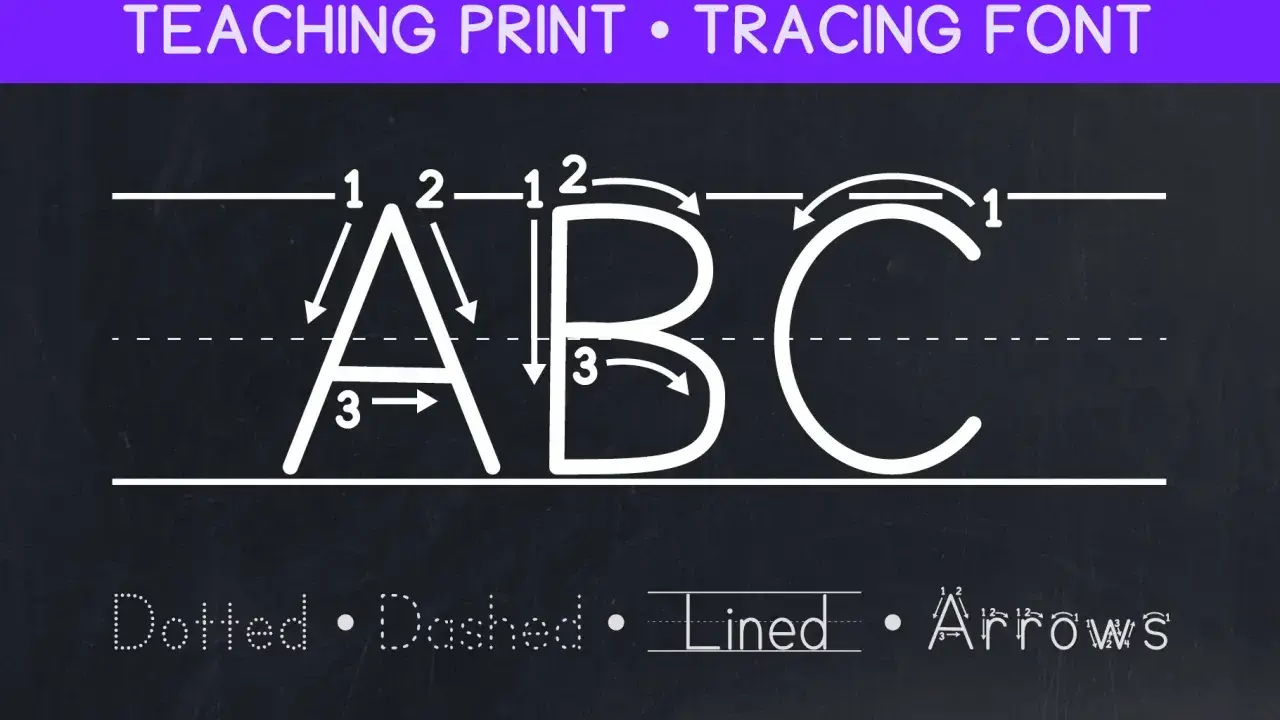
Szkolne pismo - Jak wybrać font, który wspiera naukę?
Pismo szkolne czcionka z literami ABC i strzałkami pokazującymi kierunek pisania. Pomoc w nauce pisania.
Szkolny krój pisma nie jest ozdobą, tylko narzędziem do nauki liter, łączeń i ruchu ręki. Dobrze dobrana czcionka potrafi ułatwić przepisywanie, pracę po śladzie i przygotowanie czytelnych kart pracy, a źle dobrana szybko zamienia ćwiczenie w zgadywanie kształtów. Poniżej pokazuję, jak rozpoznać sensowny krój, kiedy go używać i czego unikać, żeby materiał faktycznie wspierał naukę pisania.
Najlepsze efekty daje prosty krój, duży zapis i ograniczona liczba bodźców
• Szkolne pismo ma pomagać w nauce, a nie robić efekt typograficzny.
• Najlepiej sprawdzają się kroje z czytelnymi kształtami liter, wyraźnymi łączeniami i bez ozdobników.
• Do ćwiczeń po śladzie potrzebny jest większy zapis niż do zwykłego tekstu instrukcji.
• W kartach pracy ważniejsza od stylu jest czytelność po wydruku, także na domowej drukarce.
• Nie każdy font udający pismo ręczne nadaje się do nauki pisania.
Czym właściwie jest szkolne pismo i dlaczego nie każdy font się nadaje
Szkolne pismo to model zapisu przygotowany pod edukację wczesnoszkolną: ma pokazywać litery w sposób przewidywalny, umożliwiać ćwiczenie ruchu i budować nawyk poprawnego pisania. W materiałach dydaktycznych liczy się przede wszystkim powtarzalność formy, a nie dekoracyjność. Primarium opisuje taki krój jako obecny w elementarzach dla klas 1-3, zwykle obok prostszej czcionki do czytania.
Ja patrzę na to praktycznie: jeśli dziecko ma coś przepisać, krój musi być jednoznaczny. Każda zbędna ozdoba, zbyt fantazyjna pętla albo nieczytelne połączenie utrudnia naukę kaligrafii rozumianej jako świadome, kontrolowane kreślenie liter. To od razu prowadzi do pytania, po czym poznać, że dany font naprawdę pomaga, a nie tylko wygląda „szkolnie”.
Jak rozpoznać dobry krój do nauki pisania
Najpierw patrzę na litery podstawowe: a, e, o, m, n, u, l, ł, j i s. Jeśli one są czytelne, proporcjonalne i nie mają nadmiaru ozdobników, zwykle cały krój ma sens dydaktyczny. Jeśli już na tym etapie widać chaos, lepiej szukać dalej.
Cecha Dlaczego ma znaczenie Co wybierać
Wyraźne kształty liter Dziecko szybciej rozpoznaje znak i zapamiętuje jego formę Litery proste, bez przesadnych zawijasów
Stabilne łączenia Ułatwiają naukę płynnego pisania wyrazów Łączenia o jednolitym rytmie, bez przypadkowych skoków wysokości
Polskie znaki W języku polskim są obowiązkowe, nie opcjonalne Poprawne ą, ę, ł, ń, ó, ś, ź, ż
Brak dekoracyjnych dodatków Ozdoby odciągają uwagę od ruchu ręki Bezszeryfowe lub delikatnie odręczne formy
Dobry kontrast Litery muszą być widoczne po wydruku i na ekranie Czerń, ciemny grafit, ewentualnie wyraźna szarość
W praktyce sprawdzam też, czy krój nie zmienia się zbyt mocno między małą a wielką literą oraz czy zachowuje czytelność w mniejszym rozmiarze. Jeśli font wygląda dobrze tylko w dużym podglądzie, to przy nauce pisania zwykle przegrywa z prostszym rozwiązaniem. Właśnie dlatego sam wygląd kroju to dopiero połowa decyzji, a druga połowa dotyczy konkretnego zastosowania.
Jak używać szkolnej czcionki w kartach pracy i materiałach do druku
Największy sens ma ona tam, gdzie dziecko ma śledzić, odwzorowywać albo uzupełniać litery. W instrukcji Generatora Kart Pracy ORE pole „Pismo szkolne” jest opisane wprost jako pole tekstowe do nauki pisania, więc jego rola jest bardzo konkretna: wspiera ćwiczenie zapisu, a nie zastępuje zwykłego tekstu wszędzie i zawsze.
Sytuacja Lepszy wybór Dlaczego
Litery po śladzie Szkolny krój o dużym stopniu Dziecko widzi kierunek ruchu i kształt znaku
Nowa litera na zajęciach Jedna litera, duży zapis, dużo miejsca Mniej bodźców, łatwiejsze skupienie na formie
Łączenie liter w wyrazy Prosty model pisma odręcznego Pokazuje rytm i logikę połączeń
Polecenia i instrukcje Neutralny krój bez ozdobników Tekst ma być czytelny szybciej niż „ładny”
Dłuższy opis na stronie Prosty bezszeryfowy font Szeryfy, czyli drobne zakończenia liter, nie pomagają tu w nauce pisania
Ja zwykle trzymam się zasady jednego zadania na stronę i jednego głównego celu na arkusz. Jeśli na jednej kartce mieszam ślad, liniaturę, trzy rodzaje ozdobników i jeszcze drobny tekst objaśniający, dziecko skupia się na wszystkim naraz, a nie na ruchu ręki. Po wydruku warto też odsunąć kartę na około 1 metr: jeśli nadal wszystko jest czytelne, materiał ma szansę działać w klasie i w domu.
Jak dobrać krój do wieku dziecka i celu lekcji
Nie dobieram pisma szkolnego „na oko”, tylko pod to, co dziecko ma zrobić. Resortowe materiały edukacyjne przypominają, że nauka czytania i pisania powinna iść równolegle, a nie być przyspieszana na siłę. To ważne, bo im młodsze dziecko, tym bardziej potrzebuje prostych bodźców i większej przestrzeni roboczej.
Etap Cel materiału Praktyczny wybór